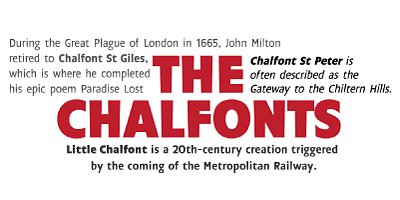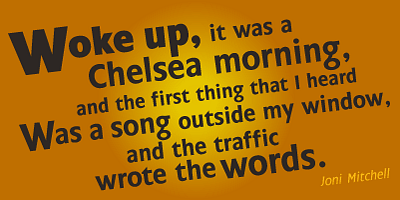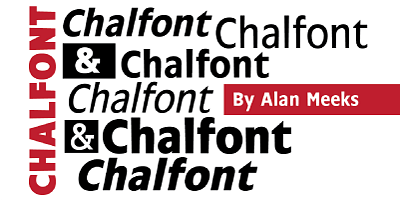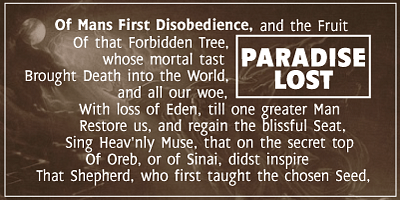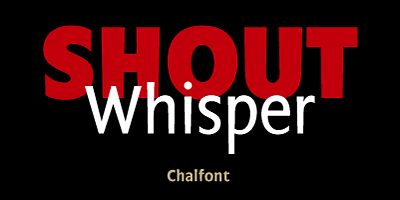
Die Schrift wurde entworfen, nachdem ich eine Fotokopie eines News Gothic-Textes gesehen hatte, bei dem die Tinte an der Unterseite der einzelnen Zeichen verblasst war. Da die Zeichenerkennung im Allgemeinen auf der oberen Hälfte eines Zeichens basiert, wurde die Lesbarkeit nicht beeinträchtigt. Ähnlich wie die Antique Olive wirken die Zeichen bei direkter Betrachtung kopflastig. Da die meisten Schriften jedoch schräg gelesen werden und der obere Teil weiter entfernt ist als der untere, wird dieser kopflastige Eindruck gemildert.